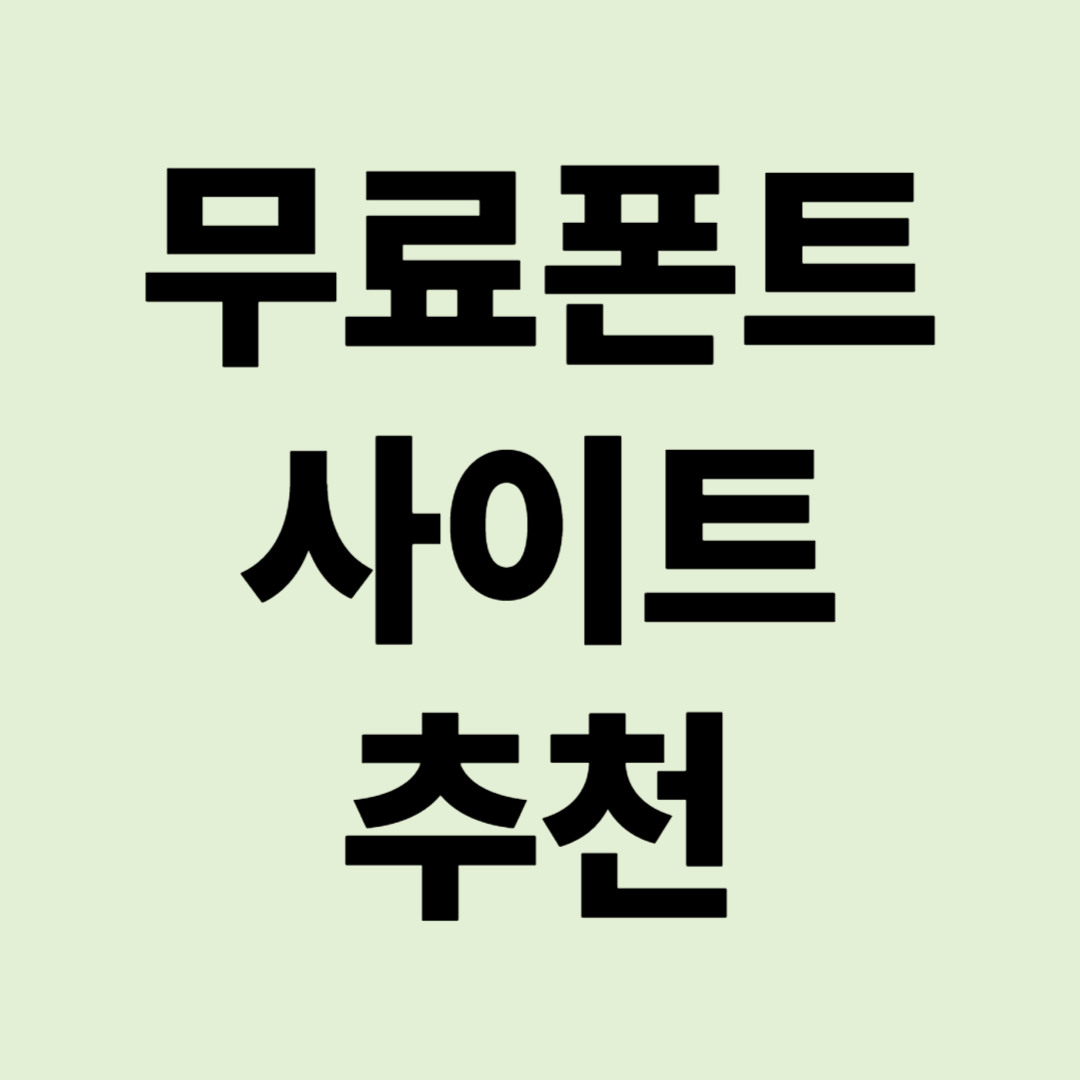
블로그, 유튜브, 썸네일, 인쇄물, PPT까지… 디자인 작업을 하다 보면 늘 필요한 것이 바로 ‘폰트’입니다.
그런데 무료라고 해서 다 같은 무료가 아닙니다.
✔ 자주 쓰는 스타일이 있는지?
이번 글에서는 2025년 기준, 많은 디자이너와 블로거들이 애용하는 무료 폰트 사이트 TOP5 를 사용 후기 기반으로 정리했습니다.
1. 눈누 (noonnu.cc)
‘무료 폰트’ 하면 가장 먼저 떠오르는 사이트입니다.
웹폰트 형식으로 제공돼 별도 다운로드 없이 HTML 코드 복붙만으로 블로그, 웹사이트에 바로 적용 가능해요.
● 200개 이상의 폰트 보유
● 디자인, 손글씨, 깔끔체, 굵은체 등 다양한 스타일
● 웹에서 바로 미리보기 가능
2. 산돌구름 무료관 (sandollcloud.com)
✔ 국내 대표 폰트 기업 산돌이 운영하는 공식 무료관
한글 디자인 업계에서 가장 많이 쓰이는 산돌체를 공식 무료관을 통해 일부 무료로 사용할 수 있습니다.
● 상업적 사용 가능한 무료 폰트 20종 이상 제공
● 깔끔하고 전문적인 인쇄용/웹용 폰트 다수
● 웹폰트 & 다운로드 병행 지원
3. 어비폰트 (uhbee.com)
✔ 귀엽고 감성적인 손글씨체를 원한다면 추천
블로그, 브이로그 자막, 감성 썸네일에 자주 쓰이는 ‘손글씨 느낌’의 대표 폰트 제공 사이트입니다.
● 네이버 폰트 검색에서도 자주 노출됨
● 감성, 레트로, 앙증맞은 스타일 위주
4. 네이버 나눔글꼴 (hangeul.naver.com)
✔ 안정성과 신뢰도 높은 공공 무료 글꼴
네이버가 제공하는 공식 한글 글꼴입니다.
● 나눔스퀘어, 나눔명조, 나눔고딕 등 다양한 굵기
● 인쇄용·프레젠테이션용 글꼴로 활용도 높음
TIP: 블로그 본문, 프레젠테이션 제목에 활용 시 깔끔하고 정돈된 느낌
5. Google Fonts (fonts.google.com)
✔ 전 세계에서 사용하는 무료 영문+한글 웹폰트 라이브러리
구글이 제공하는 오픈소스 폰트 저장소로, 한글뿐만 아니라 영문/다국어 폰트까지 한 번에 찾을 수 있습니다.
● 웹 개발자와 블로거에게 최적화
● 한글 폰트는 ‘Noto Sans KR’, ‘Nanum Gothic’ 인기
장점: 웹폰트 삽입이 매우 간편하고 속도 최적화도 잘 되어 있어 블로그나 티스토리에 활용하기 좋습니다.
결국 폰트 사이트 선택 요령으로는
✔ 본문용 vs 제목용 폰트 스타일 구분
✔ 웹폰트 or 다운로드 방식인지 사용 목적에 따라 선택
이 5곳만 알아도 블로그, 유튜브, 포스터, PPT까지 저작권 걱정 없이 자유롭게 폰트 활용이 가능합니다.